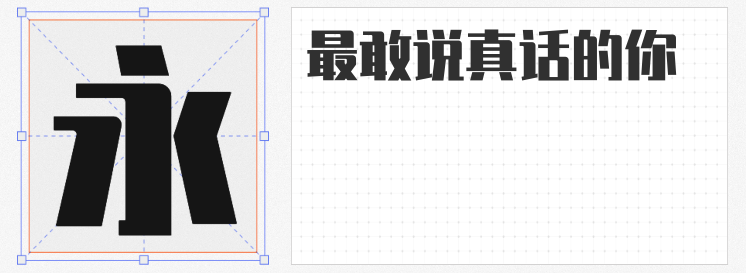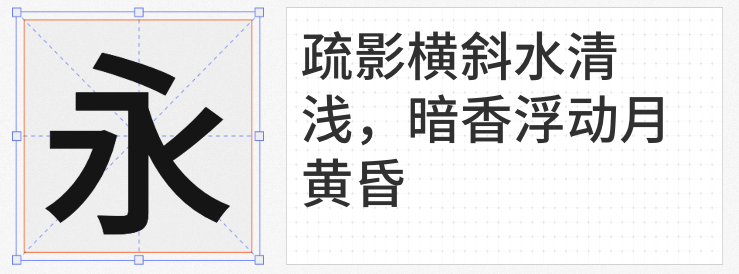
在创意设计领域,字体不仅是信息传递的载体,更是塑造视觉风格的核心元素。以下四款免费商用字体以独特的设计语言和广泛的适用性,成为设计师们打造差异化作品的利器。
以80年代手绘美术字为灵感,通过窄长字身比例和12度倾斜设计,创造出兼具人文温度与几何秩序的视觉语言。其标志性的弧线弯钩与瘦高字面,在电商海报标题、视频字幕等场景中极具辨识度。
通过笔画粗细的权重分配打破常规黑体的生硬感。在某科技公司年度报告封面设计中,该字体凭借硬朗的直角转折与12度末端倾斜,成功传递出"技术驱动未来"的品牌主张。其7567个字符的完整字库覆盖GB2312标准,确保从UI按钮到数据图表的全程应用无缺字风险。
这款融合民国美术字与现代设计理念的字体,通过直角与圆角的戏剧性碰撞,构建出独特的视觉张力。在某国潮品牌包装设计中,其笔触浑厚的横竖笔画与婉转的撇捺形成强烈对比,配合"大粗"字重营造出强烈的视觉冲击力。
作为Adobe与谷歌联合开发的泛CJK字体家族,思源黑体通过7级字重和智能排版特性,实现从手机屏幕到户外广告的无缝适配。
这四款字体通过差异化设计策略,在保持高辨识度的同时实现跨场景应用。设计师可根据项目气质灵活组合,打造兼具功能性与艺术性的视觉解决方案。